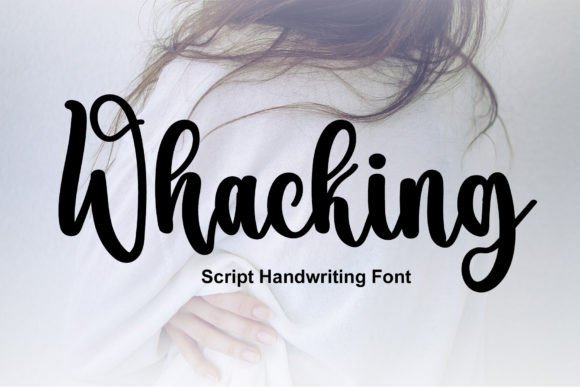
Whacking
Whacking – A Fonte Bouncy que Transforma Seu Artesanato
Se você está em busca de uma tipografia que una estilo, energia e delicadeza, Whacking é a escolha perfeita. Esta fonte bouncy traz um toque vibrante e ao mesmo tempo elegante, ideal para projetos de craft personalizados. A seguir, descubra por que Whacking está conquistando designers, artesãos e criadores de conteúdo no Brasil.
- Design estiloso e moderno – As linhas curvas e o “bounce” natural das letras dão vida a qualquer layout, tornando-o visualmente atraente.
- Versatilidade criativa – Funciona perfeitamente em convites, etiquetas, estampas de camisetas, cartões de visita e até em embalagens de produtos artesanais.
- Leitura fácil – Apesar do aspecto decorativo, a fonte mantém boa legibilidade, o que é essencial para mensagens claras em artesanato personalizado.
Ao escolher Whacking, você garante um acabamento elegante e doce ao mesmo tempo, proporcionando ao seu público uma experiência visual memorável. Experimente agora e veja como esta fonte pode elevar seu próximo projeto de craft a um nível profissional.